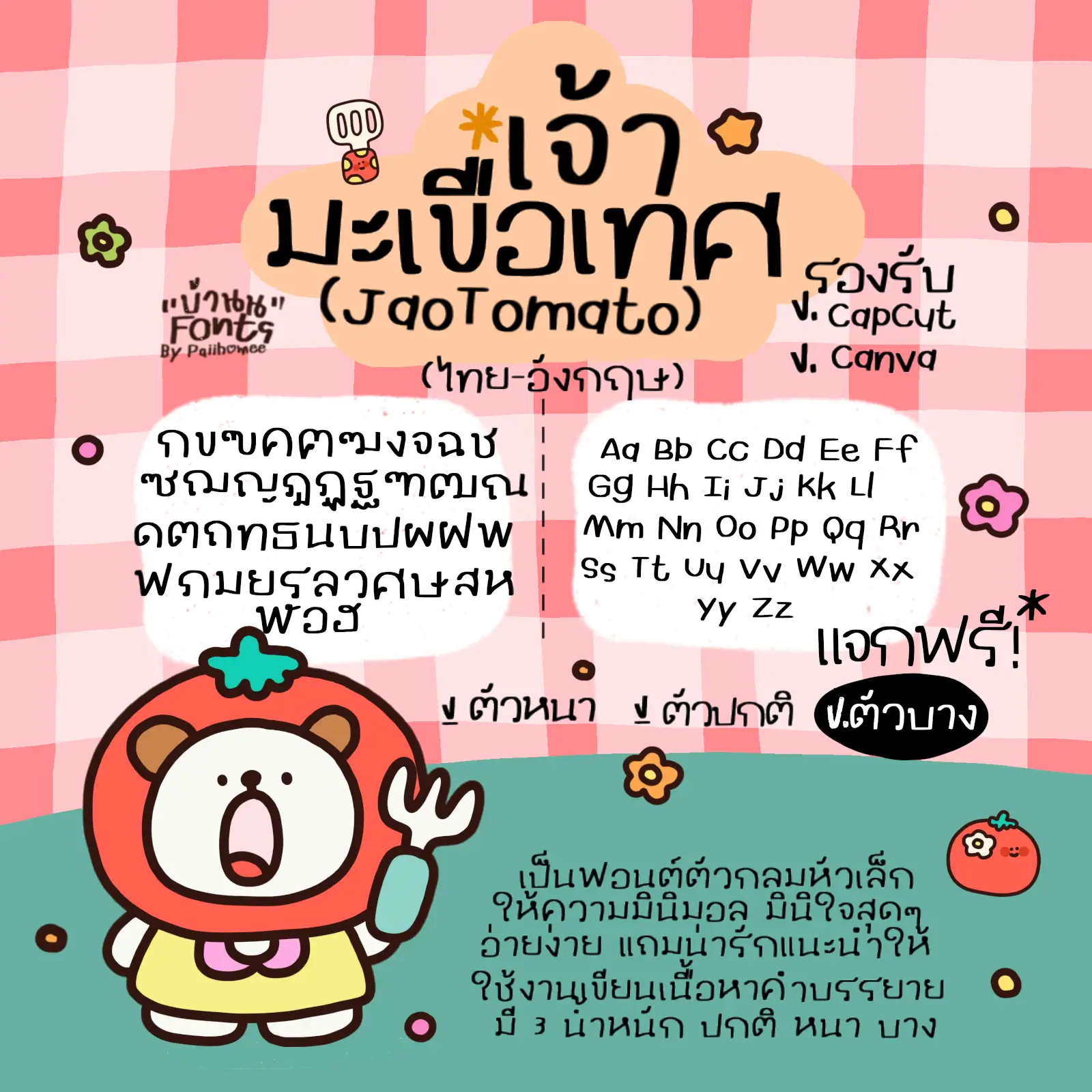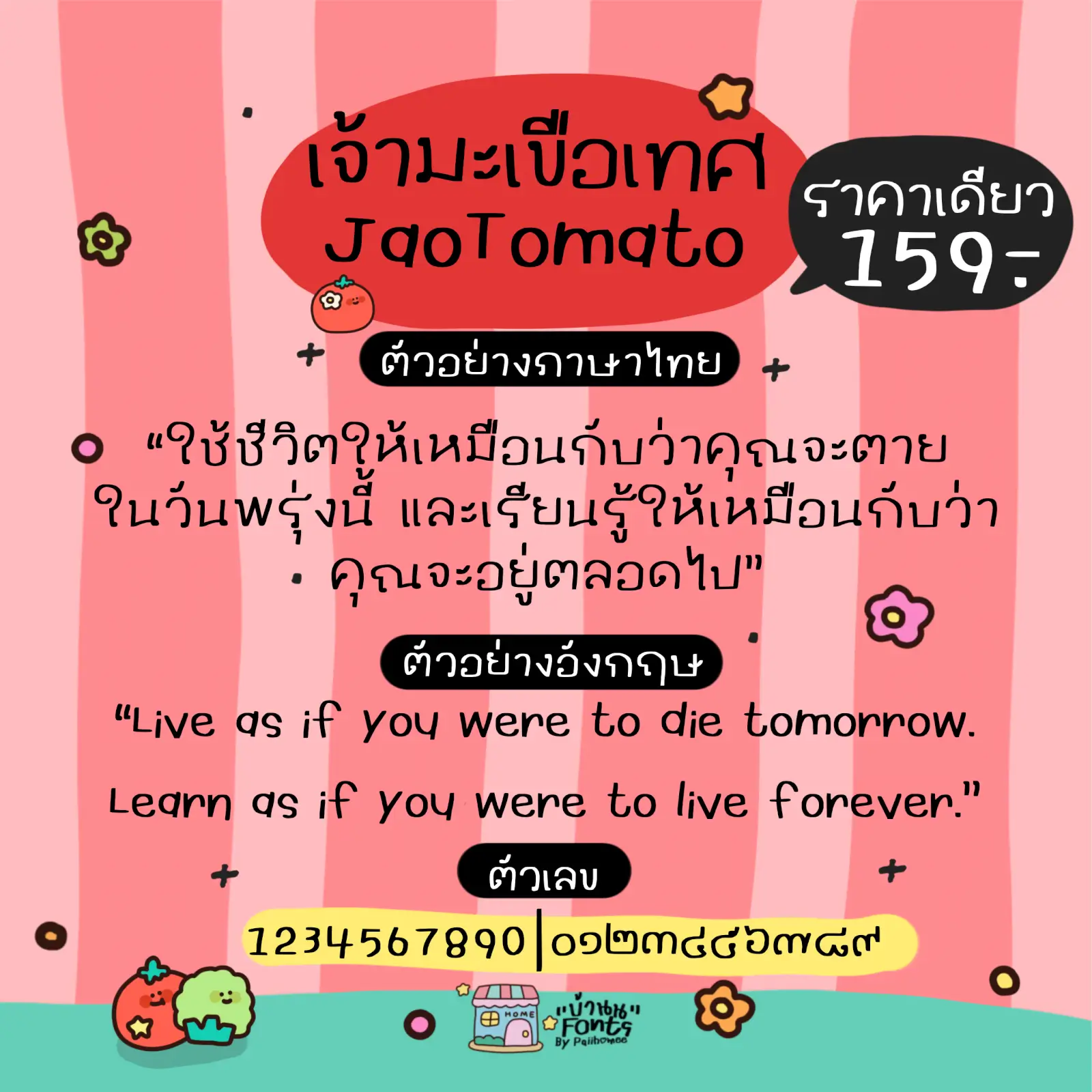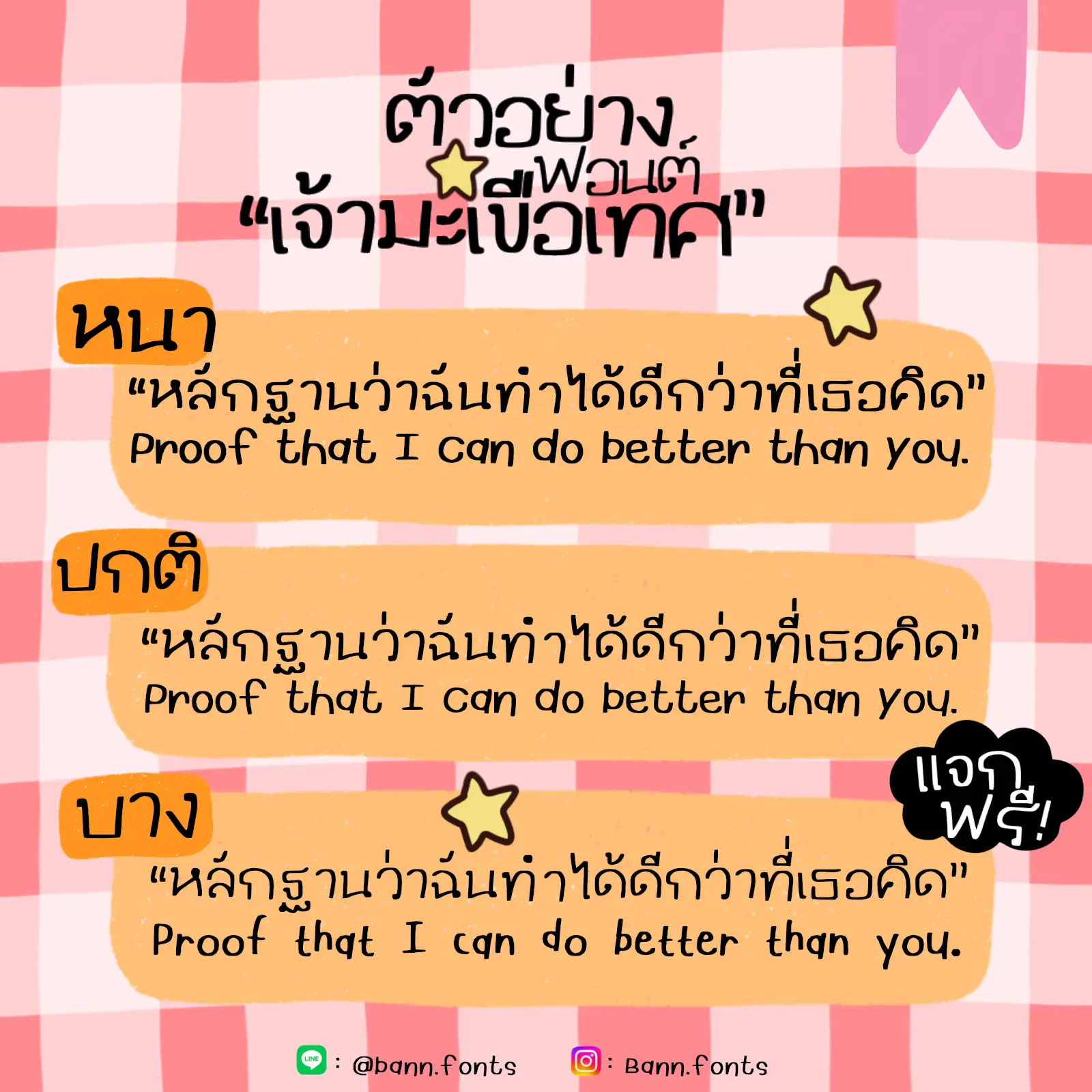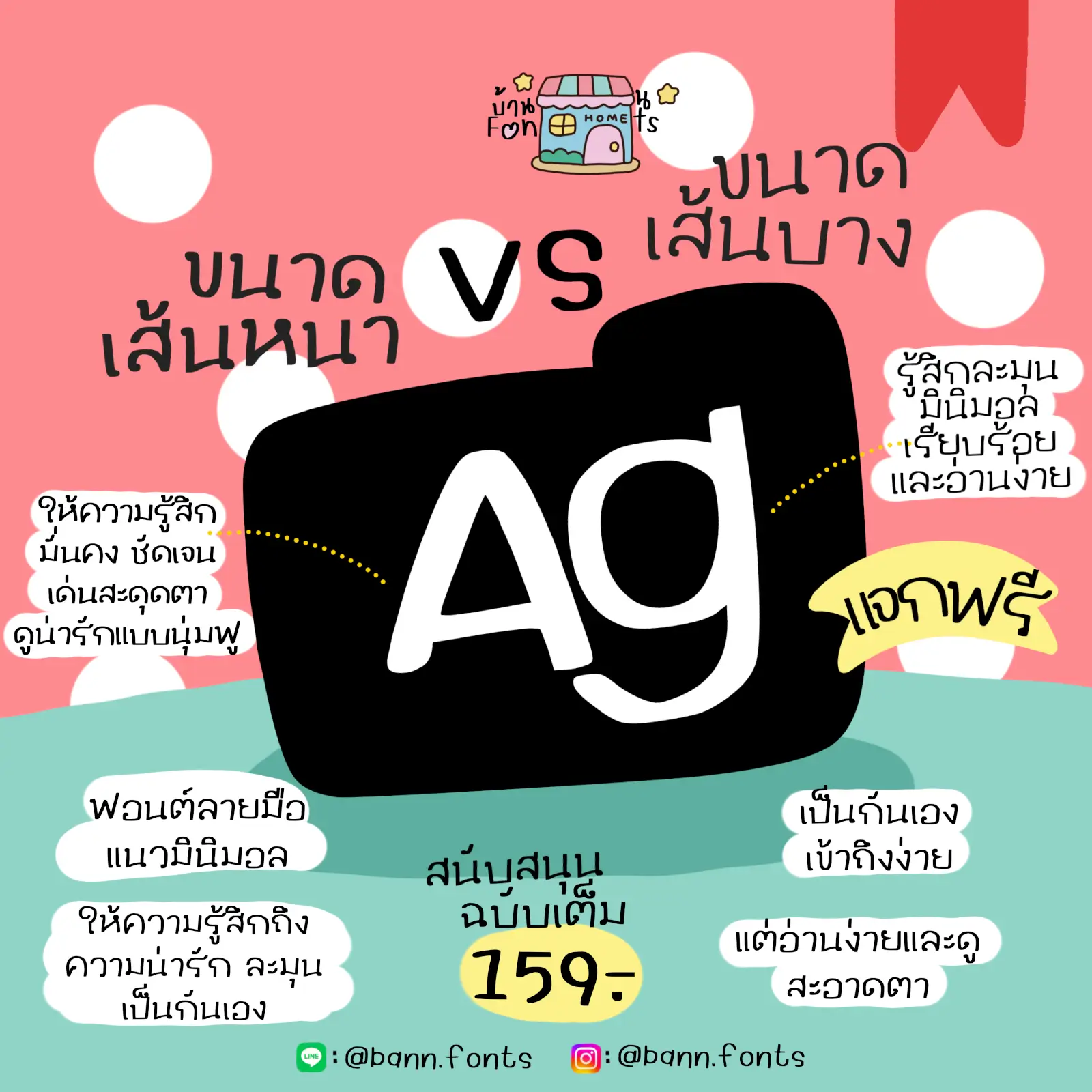
แจกให้ใช้งานฟรี! สำหรับคนที่ชอบฟอนต์ลายมือ น่ารักๆ เรียบร้อยแต่ซุกซน
เพิ่มความน่ารัก x10! ต่อยอดทำปกคลิป แต่งสตอรี่ หรือใส่รีวิวสินค้าคือจึ้งงง
แนะนำว่า นำไปใช้งานกับการจดเนื้อหา สรุปงาน จดโน้ต จดบันทึก
หรือจะนำไปทำคลิป แต่งรูป ก็เริ่ดสุดๆ แนะนำเลย
เจ้ามะเขือเทศ (JaoTomato)